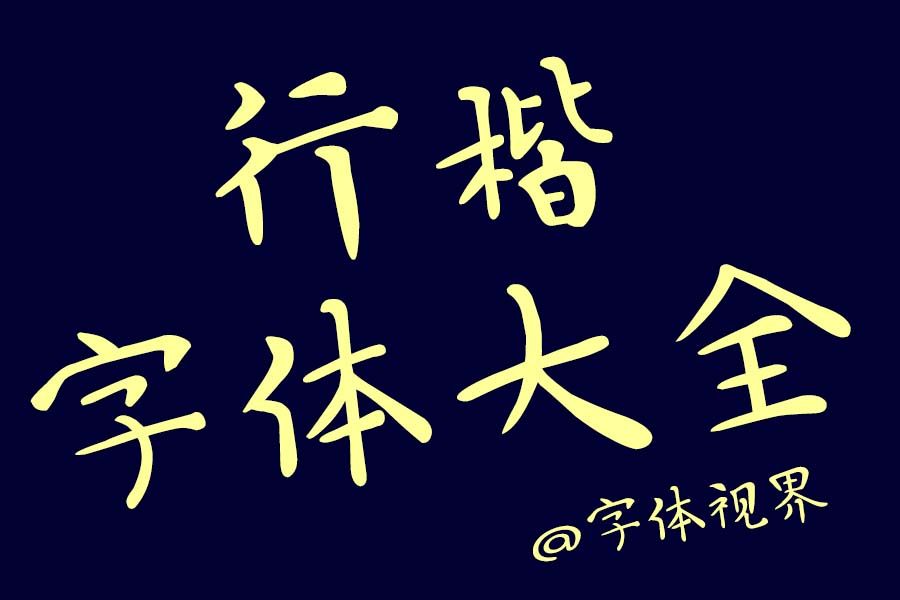
行楷字体本身是比较有艺术设计感的字体,这款字体非常的漂亮,深受一些书法爱好者的喜欢,那么书法爱好者们去哪里下载行楷字体大全呢?想要下载行楷字体大全的书法爱好者们可以去网上下载,网上的行楷字体比较全,而且有些行楷字体非常好看。
行楷字体大全里的字体设计都比较漂亮,本身行楷字体就是行书和楷书的结合,所以不少爱好书法的人,都喜欢练习这种行楷字体。
行楷字体大全很适合书法爱好者,但是书法爱好者在学习行楷字体的时候也要注意楷书字体的通病。楷体的字体结构比较方正,在练习的时候最讲究法度,所以这种字体会比较的平板,没有生气,现在不少书法爱好者都会选择一些比较夸张,或者是一些有对比的手法来解决这种字体的缺憾。但是在解决的同时又往往因为太过于夸张,或者是对比不当造成楷书字体形态怪异,或者是字体显得剑拔弩张,没办法让人感觉到字体的意蕴幽深。
行楷字体大全对有很多爱好书法的人来说确实是不错的选择,在练习的时候也需要讲究宾主相安的原则。在写一种字体的时候一定要树立主笔画的意识,一个字之内必须要主次分明,就像是日月星辰一样都有自己各自的位置。如果这个位置不对了,那么给人的感觉也会不一样,所以主笔画就如同有了引领意义一般,而行楷字体的艺术风格也因为主笔画的引领而变得不一样,拥有了非常出众的艺术风格。书法爱好者在选择行楷字体的时候,也应该考虑到这些问题,这样写出来的字才会显得质朴古雅,或是挺拔伟岸。